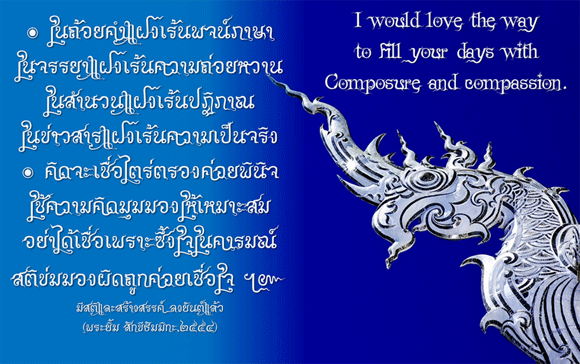
Alsmile Arounvilas
ฟอนต์ “ออลสไมล์ อรุณวิลาศ”
ฟอนต์นี้มีลักษณะพอสรุปไว้ในคำว่า เติมเต็มจิตวิญญาณความเป็นศีลปะลงในศาสตร์แห่งอักขระความเป็นไทย
“หยั่งลึกปฐวี วารีไหล ลมไสว เปลวไฟสบัด หัวใจปรมัตถ์และความสว่างชัดแห่งปัญญาญาณ”
เป็นฟอนต์ที่ทำขึ้นมาจากการฝึกเรียนรู้ที่จะบริโภคเทคโนโลยีด้วยปัญญา
ท่านสามารถใช้ในงานพิมพ์ทั่วไปได้ตามความเหมาะสมและเข้ากับลักษณะงาน